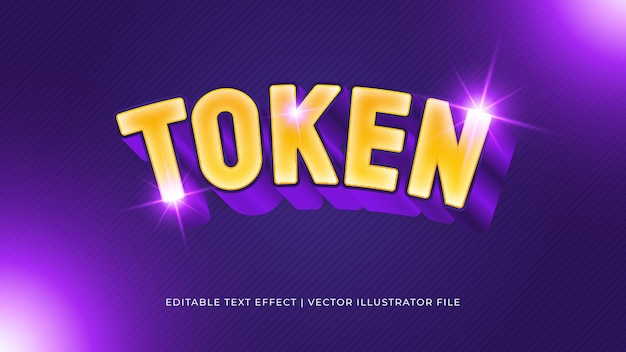
Технология токена, редактируемый текстовый стиль, стиль текста, современная технология синего блокчейна, редактируемый текстовый эффект, яркий современный цвет, блестящий Эффект стиля текста, редактируемые шрифты, векторные файлыТехнология токена, редактируемый текстовый стиль, стиль текста, современная технология синего блокчейна, редактируемый текстовый эффект, яркий современный цвет, блестящий Эффект стиля текста, редактируемые шрифты, векторные файлы
Технология токена, редактируемый текстовый стиль, стиль текста, современная технология синего блокчейна, редактируемый текстовый эффект, яркий современный цвет, блестящий Эффект стиля текста, редактируемые шрифты, векторные файлы